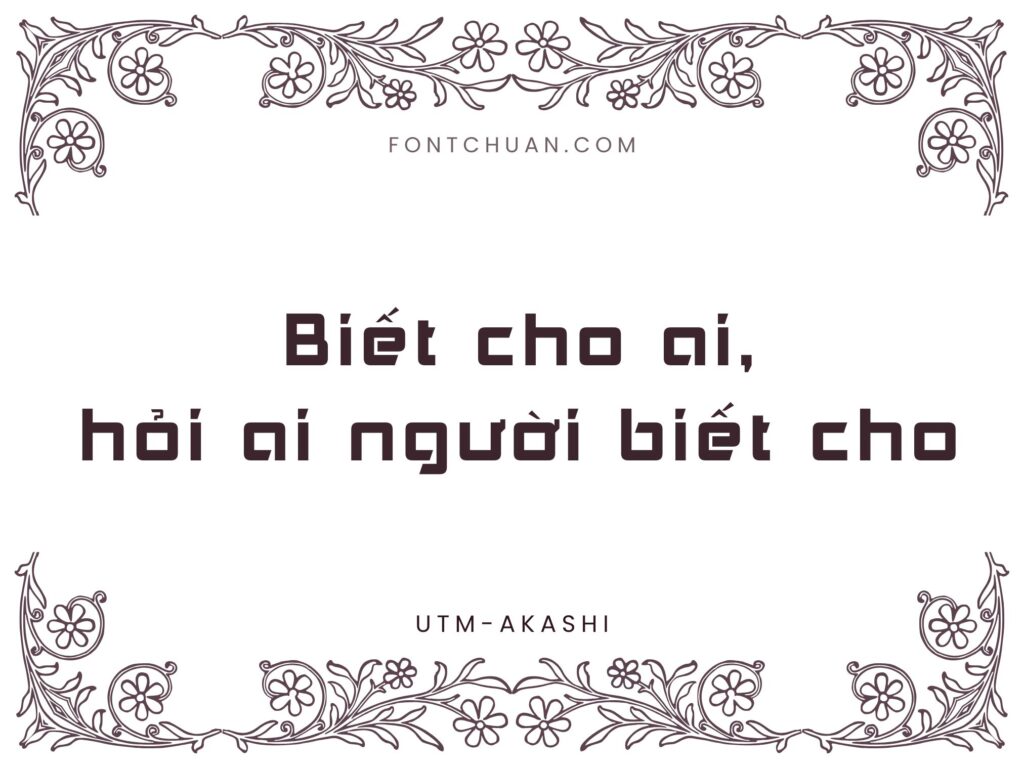
Font UTM Akashi Việt Hóa
UTM Akashi là một kiểu chữ hiện đại mang tính trang trí cao, được thiết kế bởi Michael Đinh Kiên. Với các chi tiết độc đáo và hình khối rõ ràng, font này còn được xếp vào nhóm Font Decorative, giúp các thiết kế trở nên nổi bật và cá tính hơn. UTM Akashi có phong cách mạnh mẽ, cấu trúc phá cách và hỗ trợ đầy đủ tiếng Việt cùng với hơn 100 ngôn ngữ khác. Đây là một trong những font được thành viên của Font Chuẩn sưu tầm và chọn lọc nhằm phục vụ nhu cầu thiết kế đa dạng, đặc biệt trong các dự án sáng tạo, truyền thông thị giác và nhận diện thương hiệu.
UTM Akashi có cấu trúc chữ đậm, các đường cắt sắc sảo, tạo cảm giác chắc chắn và hiện đại. Font thích hợp sử dụng trong các tiêu đề lớn, thiết kế logo, áp phích, bao bì sản phẩm hoặc banner kỹ thuật số. Sự độc đáo trong tạo hình chữ khiến Akashi dễ dàng trở thành điểm nhấn thị giác trong mọi thiết kế. Những ngành nghề như quảng cáo, công nghệ, giáo dục và bất động sản đều có thể ứng dụng font này để tăng tính nhận diện và sức hút của sản phẩm.